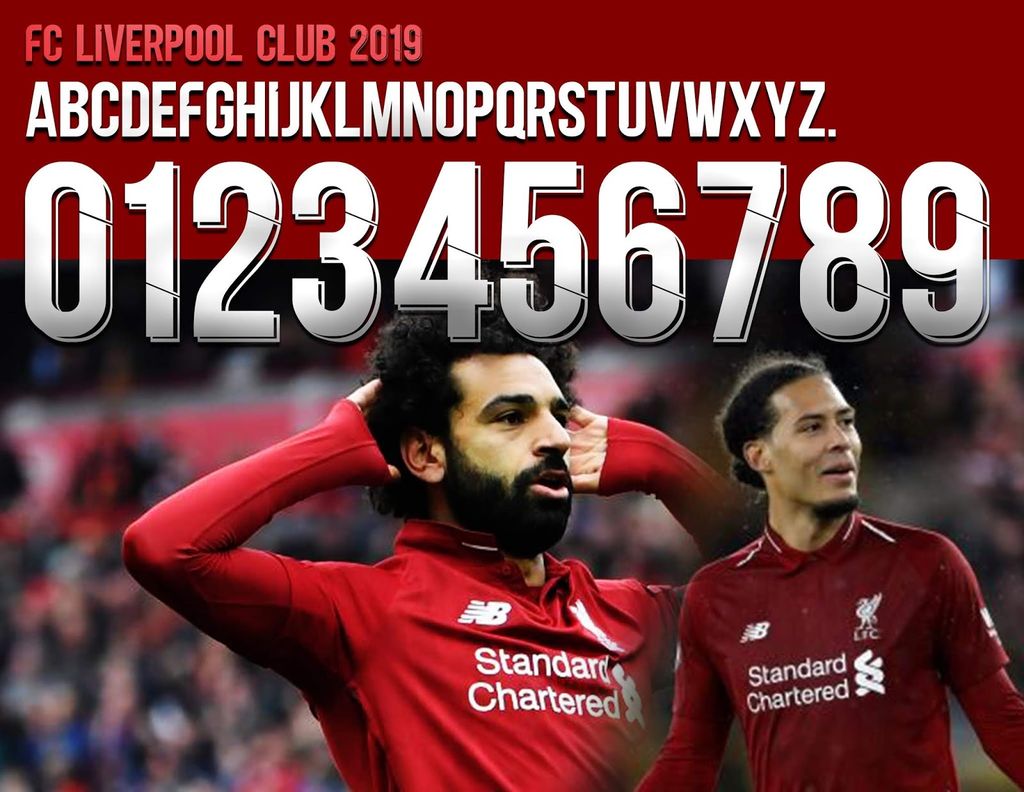
Một chiếc áo bóng đá đẹp ngoài việc đáp ứng các yêu cầu về chất liệu có độ co giãn, thấm hút tốt và thiết kế trẻ trung hiện đại thì chọn lựa font số cũng là một điều quan trọng bạn cần chú ý khi đặt in áo theo đội.
Dưới đây là những mẫu font số đẹp được yêu thích nhất trên thị trường hiện nay. Nếu bạn đang phân vân trong việc lựa chọn font số cho áo bóng đá, hãy cùng Bulbal tham khảo những mẫu font dưới đây nhé!
FONT SỐ CÁC ĐỘI TUYỂN QUỐC GIA
Font số áo bóng đá UEFA Euro 2020:
Font chữ và số áo bóng đá sử dụng chính thức tại Euro 2020
Font số áo đẹp Puma:
Font chữ và số áo bóng đá đẹp Puma được hãng sử dụng theo quy chuẩn của FIFA. Những quốc gia có mẫu áo dùng font số này gồm các đội tuyển: Italia, Áo, Thụy sĩ, Cộng Hòa Séc.
Font chữ và số áo bóng đá Puma
Font áo bóng đá Adidas World Cup 2018
Tất cả các đội tuyển được tài trợ bởi Adidas sử dụng font số bóng đá Adidas World Cup 2018 truyền thống này. Gồm: Nga, Tây Ban Nha, Đức, Argentina,…
Font áo bóng đá Adidas World Cup 2018
FONT SỐ CÁC CÂU LẠC BỘ NỔI TIẾNG
Font số áo bóng đá CLB Juventus:
Sau giải Serie A, CLB Juve quyết định sử dụng phông chữ này in trên áo sơ mi cũng như áo bóng đá thi đấu, đây là một trong những font số được nhiều người ưa thích.
Font số áo bóng đá CLB Juventus
Font số áo bóng đá CLB Barcelona:
Sau mùa giải World Cup 2018, Adidas đã cung cấp phông chữ được nhiều người yêu thích bóng đá ưa chuộng, trong đó có CLB Barca.
Font số áo bóng đá CLB Barcelona
Font số áo bóng đá Inter Milan